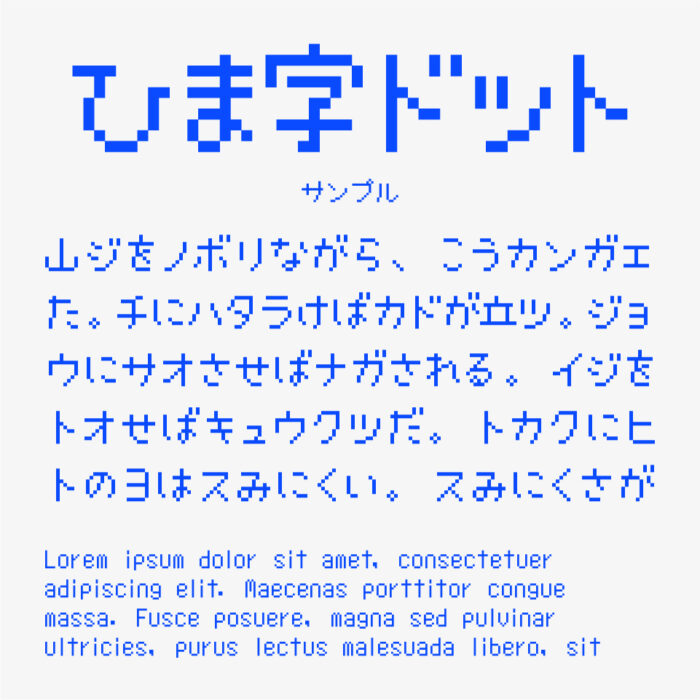
KFひま字ドット
KFひま字ドットフォントは、手書き風フォント「KFひま字」をベースにドット化されたフォントです。
ひま字の幼くて可愛らしい雰囲気はそのまま継承され、ピクセル調にリデザインされています。懐かしさと可愛らしさが絶妙なバランスの素敵なフォントです。
収録文字は、漢字(小学1年生で習う80字+α)・ひらがな・カタカナ・アルファベット・数字・記号が収録されています。